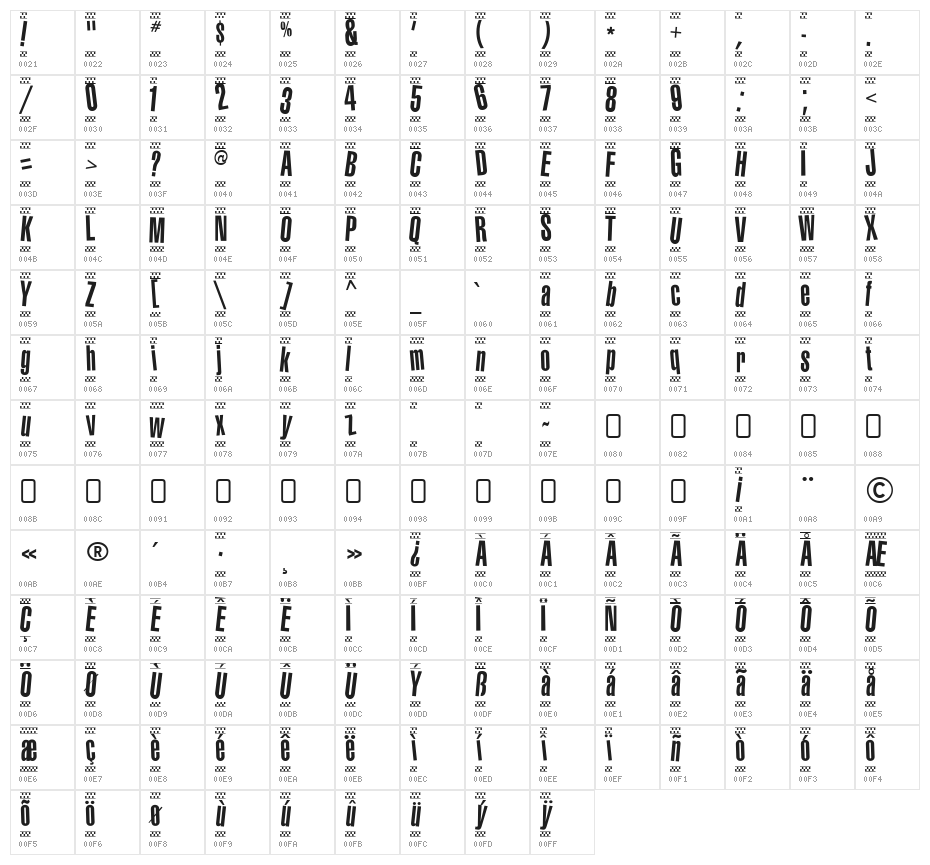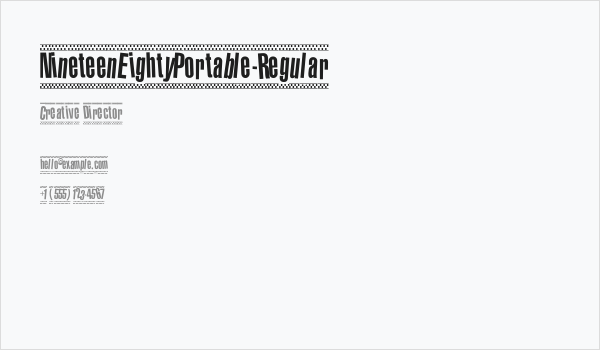
NineteenEightyPortable-Regular Font
| Progetti proposti | Ideal for retro-themed posters, branding, headlines, and any design requiring a bold statement. |